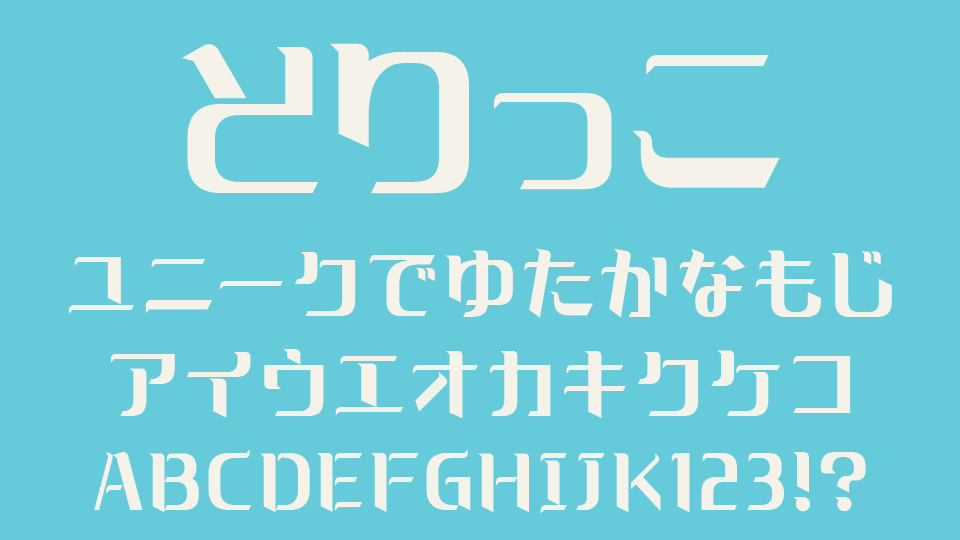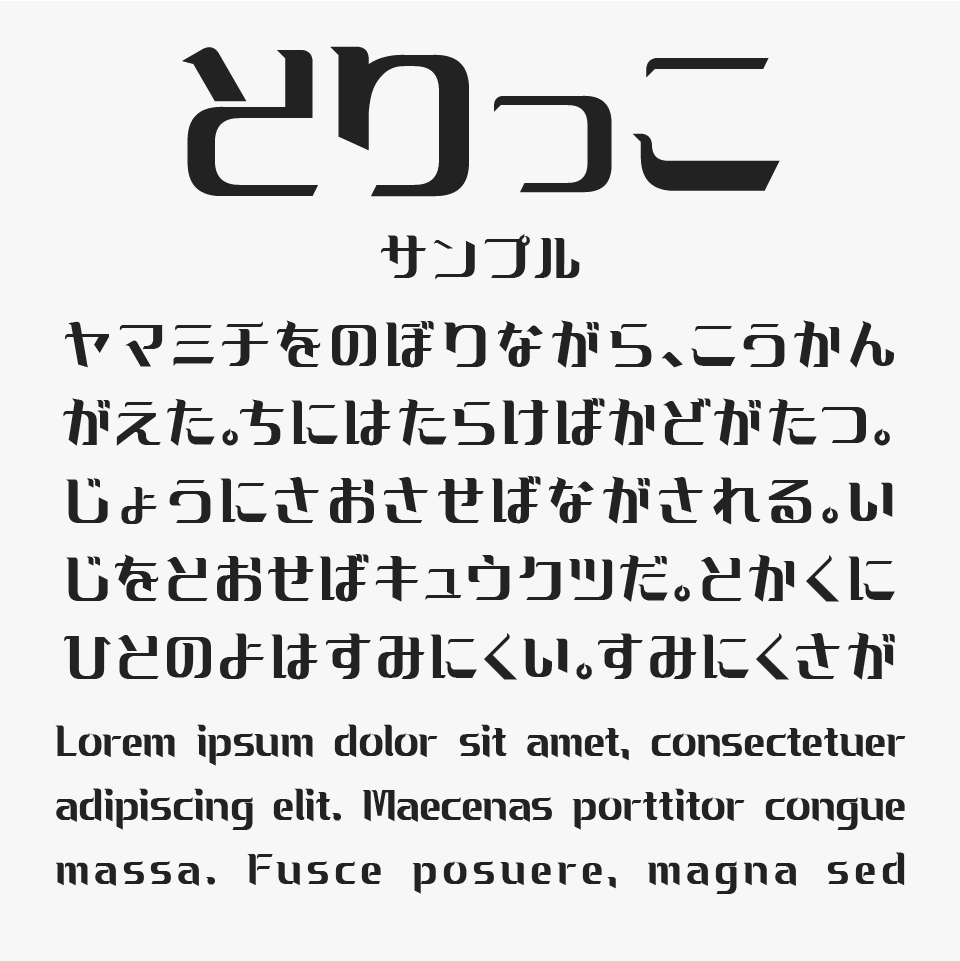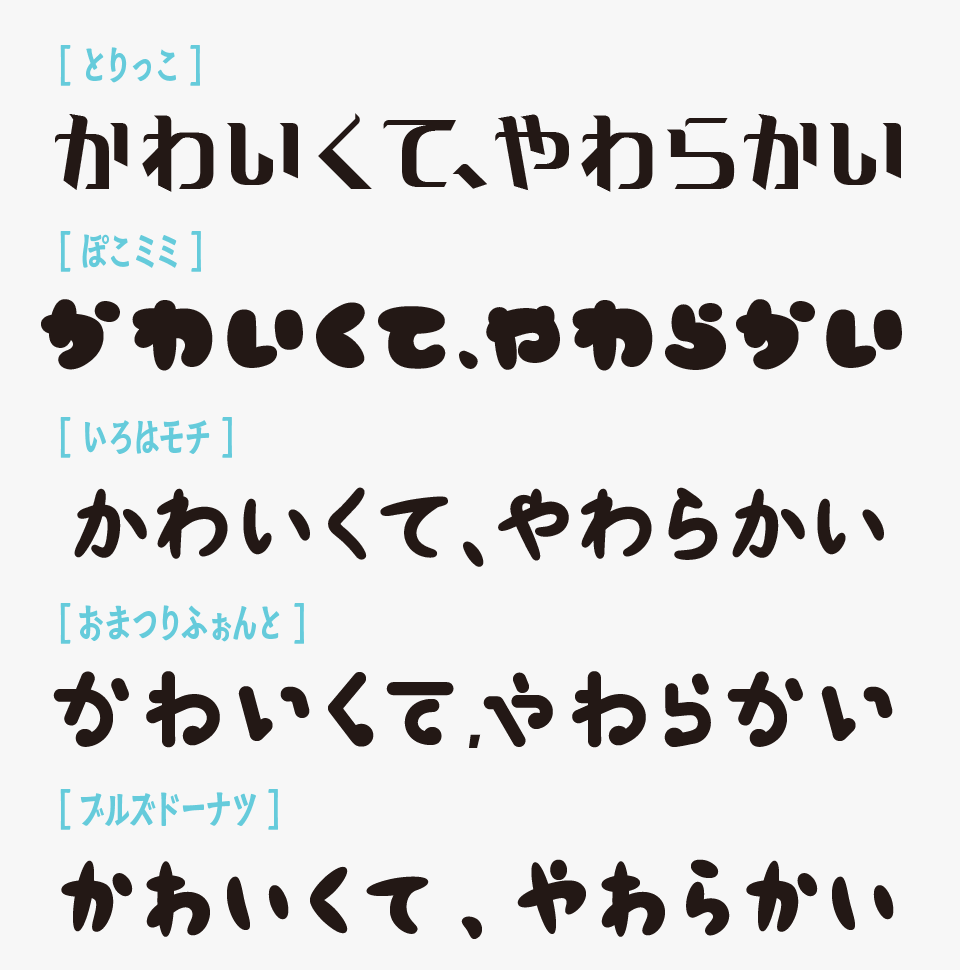
とりっこ
とりっこフォントは、小鳥のくちばしを思わせる小さな三角形の飾りが随所にあしらわれた、遊び心あふれるデザインフォントです。
文字の一部にくちばしのようなアクセントとなっていることで、さりげない可愛らしさが見ていてほっこりするようなフォントです。甘くなりすぎない洗練されたデザインなので、子ども向けから雑貨デザインまで幅広く使いやすいフォントです。
動物や自然をテーマにしたデザインをはじめ、絵本や児童向けコンテンツ、雑貨、カフェ、パッケージデザインなどにぴったりなフォントです。小鳥をモチーフにした愛らしいディテールが作品全体にやさしい雰囲気を添え、見る人の心をほっと和ませてくれるそんな魅力があるフォントです。
とりっこフォントを、ほかのやわらかくて可愛いフォントと比較してみると、小鳥のような愛らしさを感じる、ころんとしたシルエットが特徴のフォントです。
比較フォントは、「ぽこミミ」「いろはモチ」「おまつりふぉんと」「ブルズドーナツ」と使用していますが、どれも可愛らしいフォントなので、ぜひあわせてチェックしてみてください。
収録文字は、ひらがな・カタカナ・アルファベット・数字・記号が収録されています。